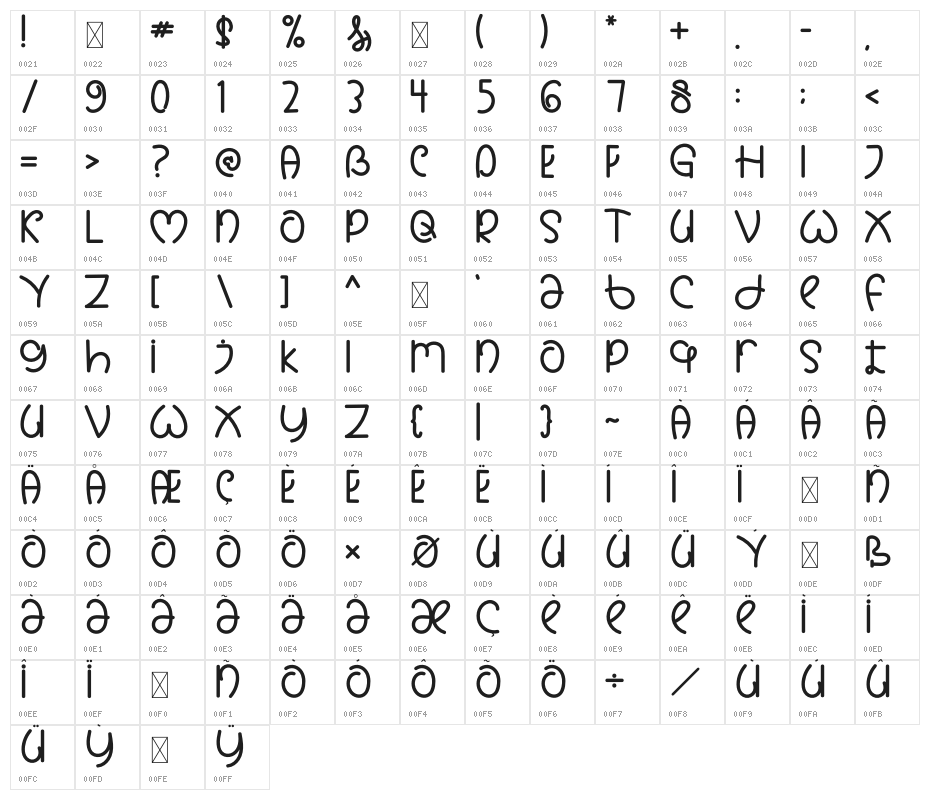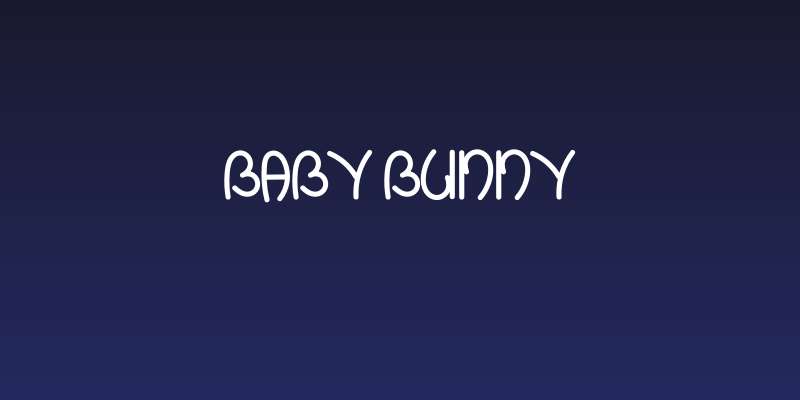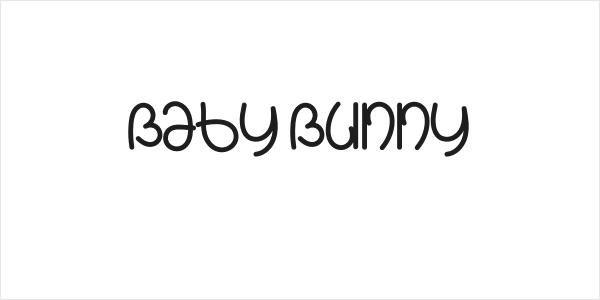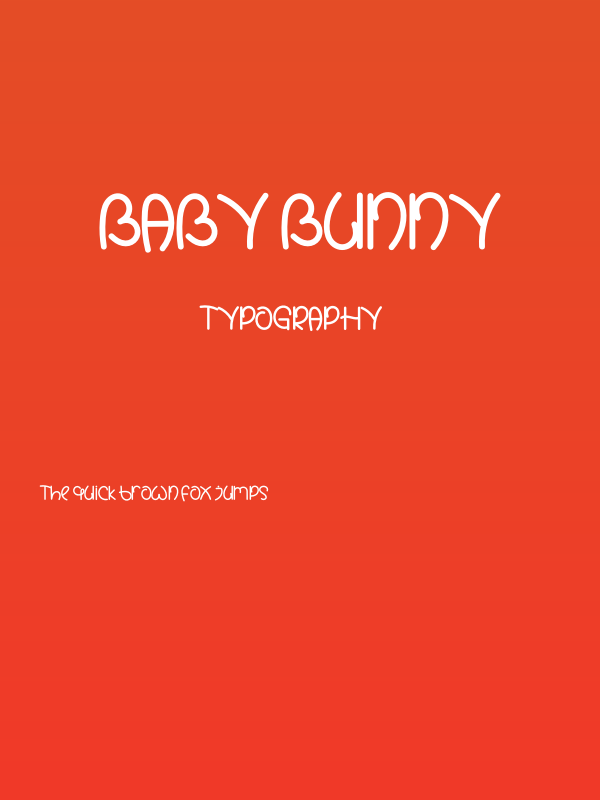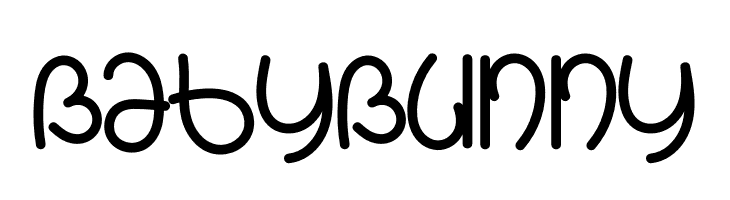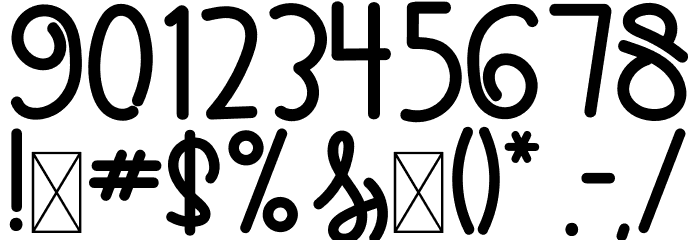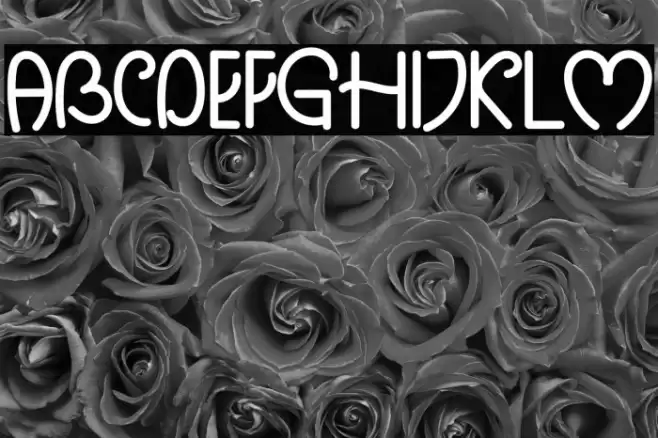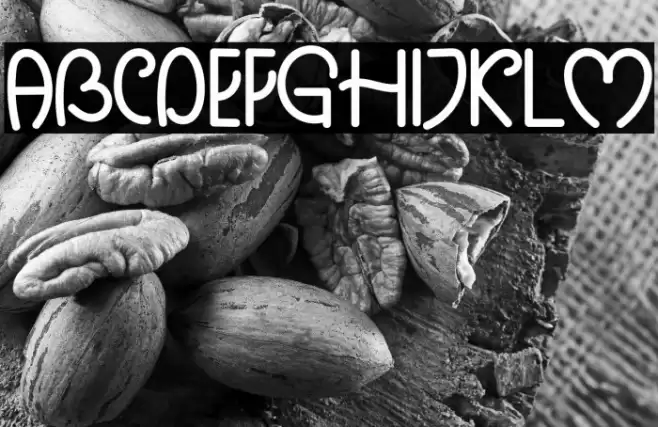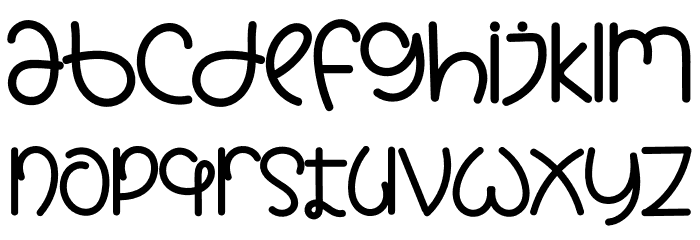
Baby Bunny Font
| Gesamtstil | Playful |
| Anwendungsfall | Headlines, Logos, Children's materials |
| Vorgeschlagene Projekte | Ideal for children's books, playful branding, greeting cards, and educational materials. |